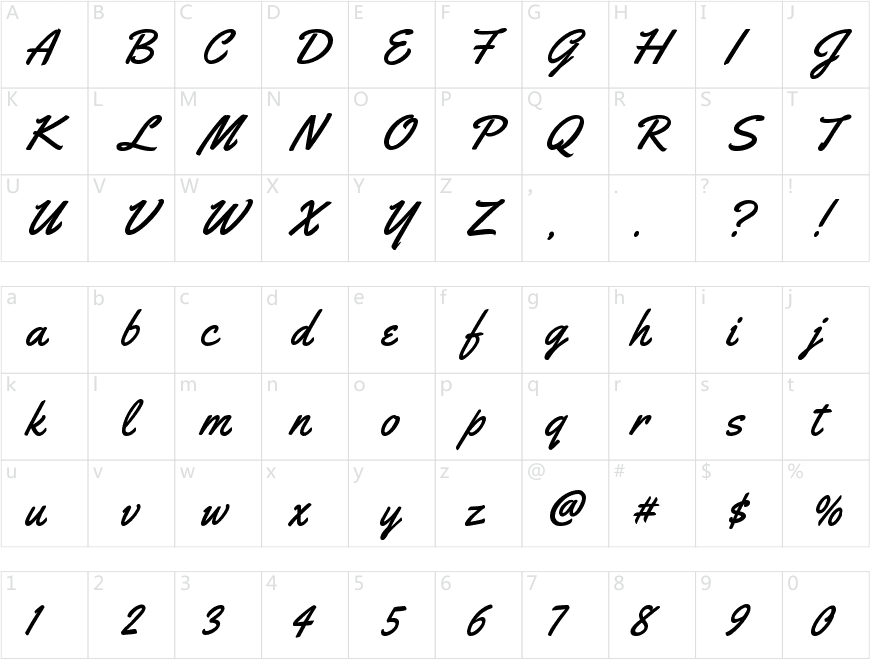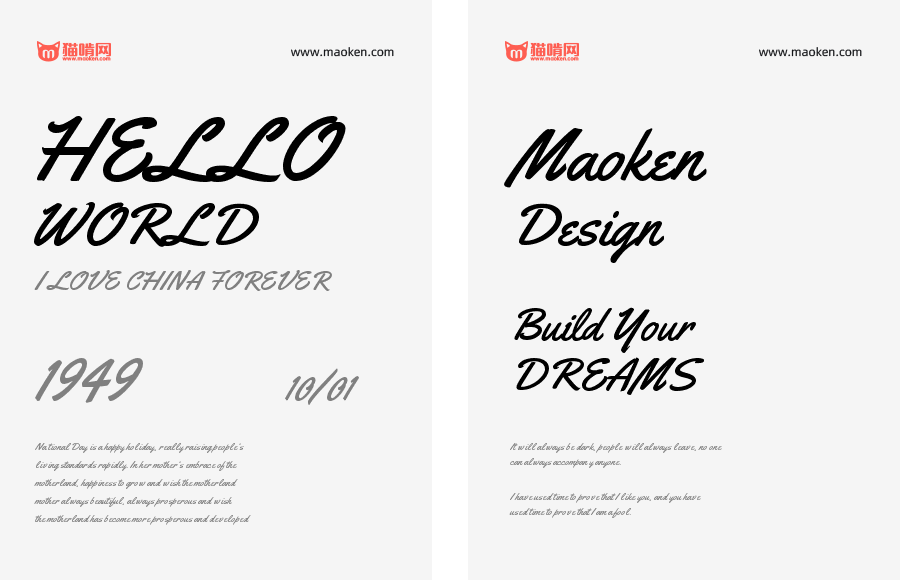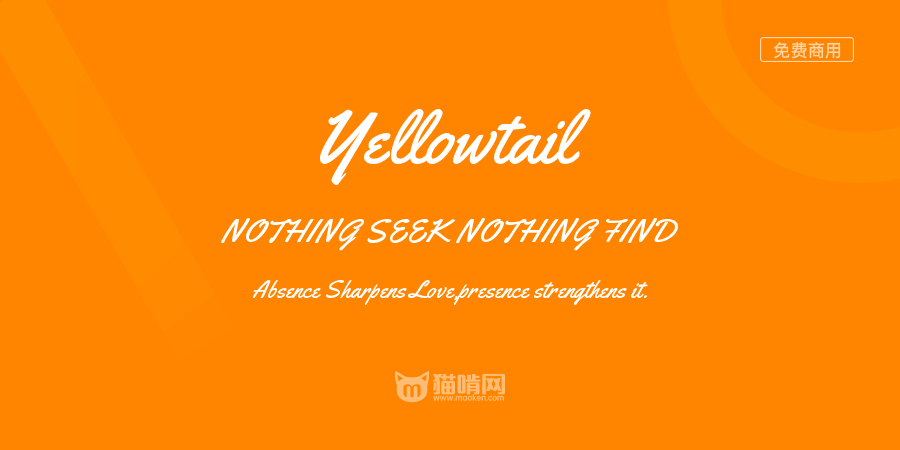
Yellowtail
Yellowtail是一款充满复古风情、采用扁平笔刷风格的手写字体,中等重量。它融合了连接和非连接两种字母形式,从而呈现出独特的外观并保证了良好的可读性。Yellowtail借鉴了经典的1930年代字体风格(如Gillies Gothic和Kaufmann),同时,它的视觉效果又带有招牌画家手写字体那种随性的节奏。